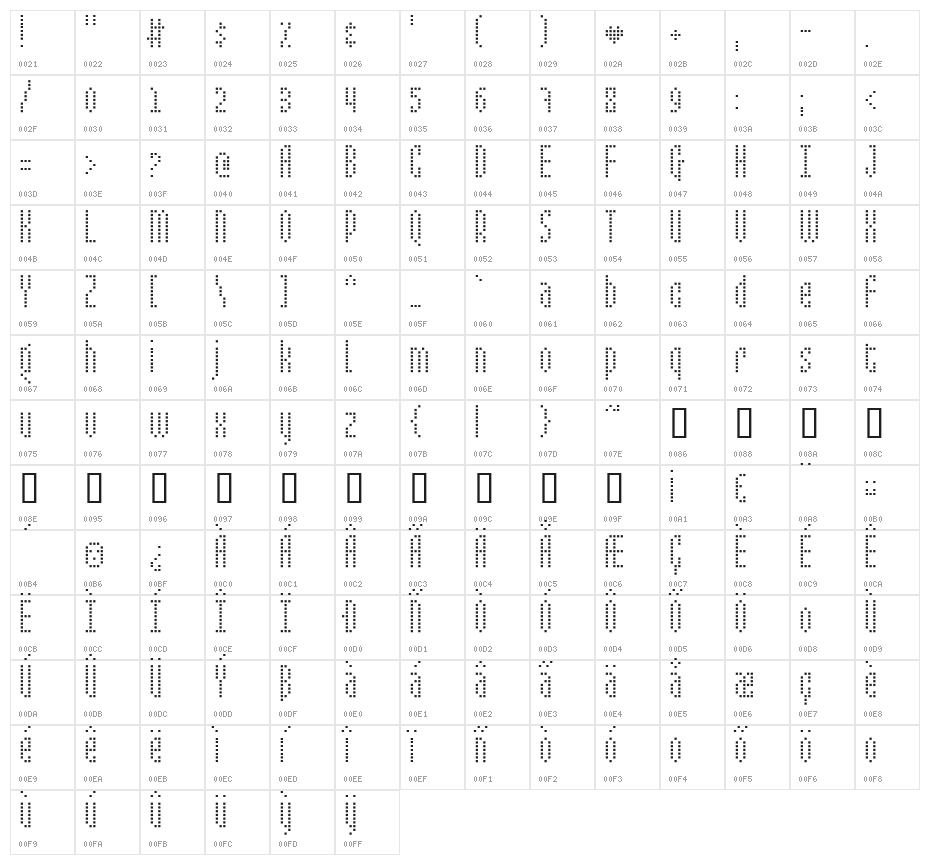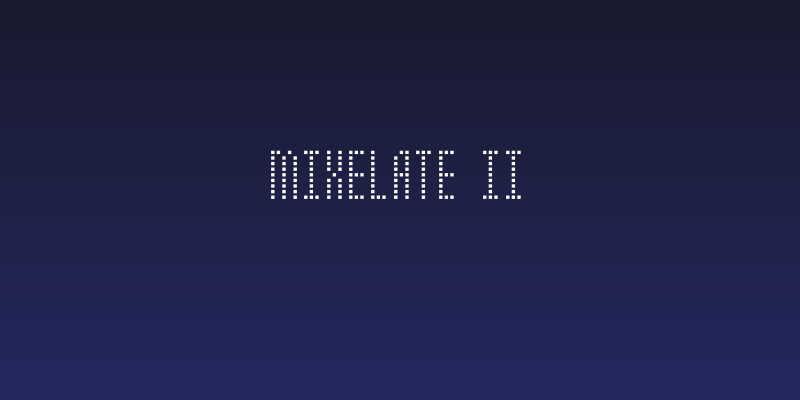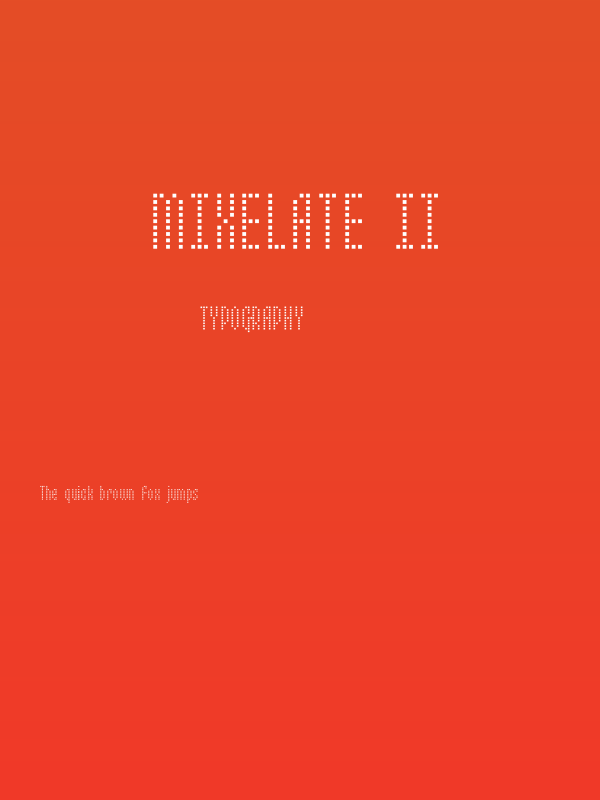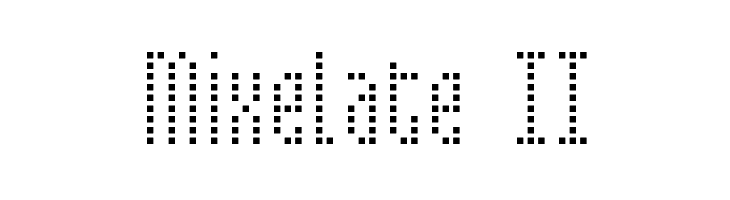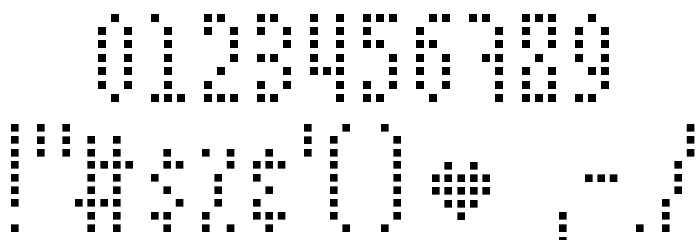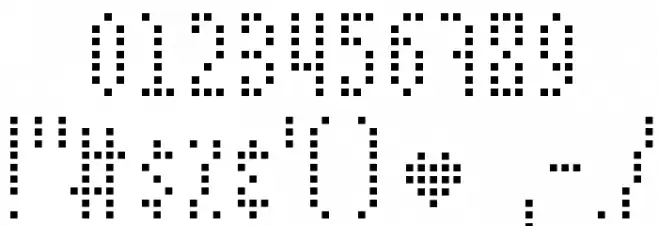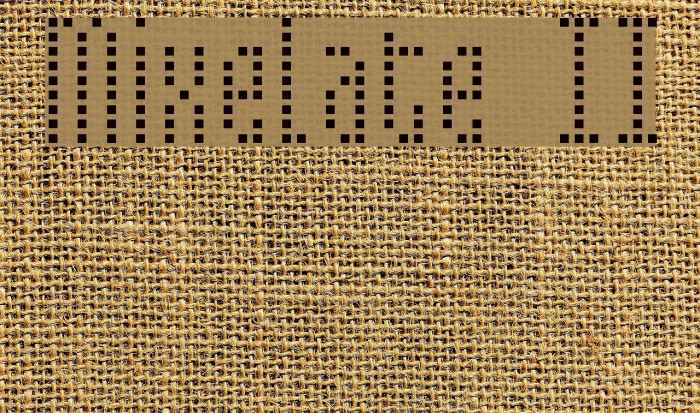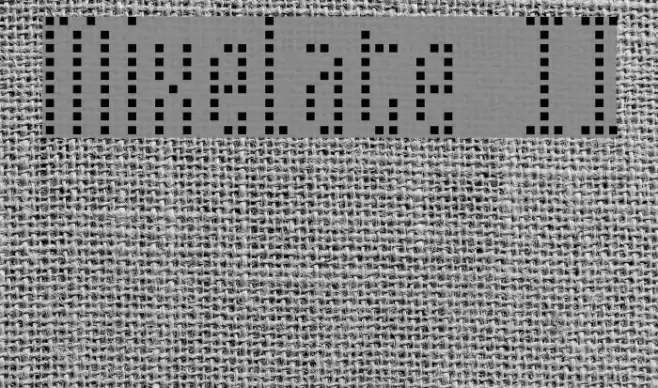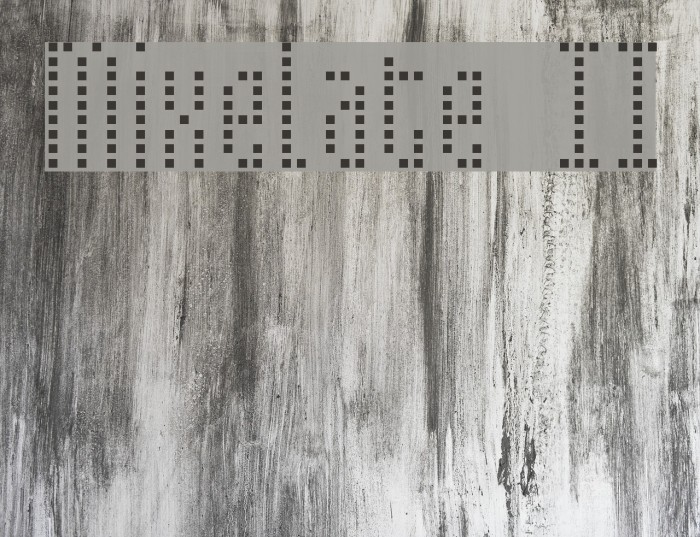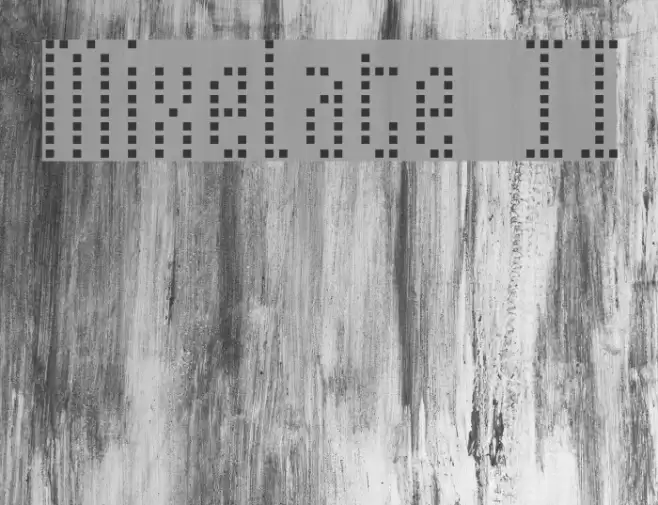
Mixelate II Font
✎ Dotted
| カテゴリ | Dotted |
| 全体的なスタイル | Retro, Digital |
| 用途 | Headlines, Logos, Digital Art |
| おすすめプロジェクト | Ideal for video game design, digital art projects, retro-themed posters, and tech-related branding. |